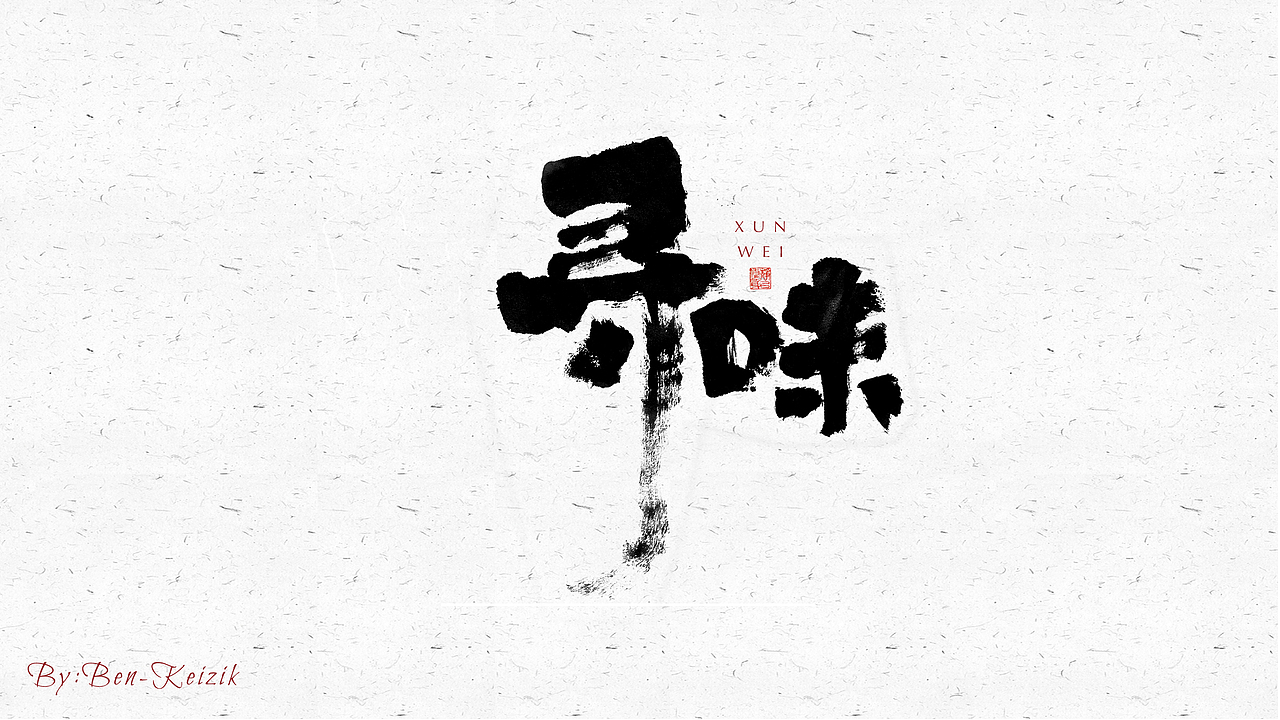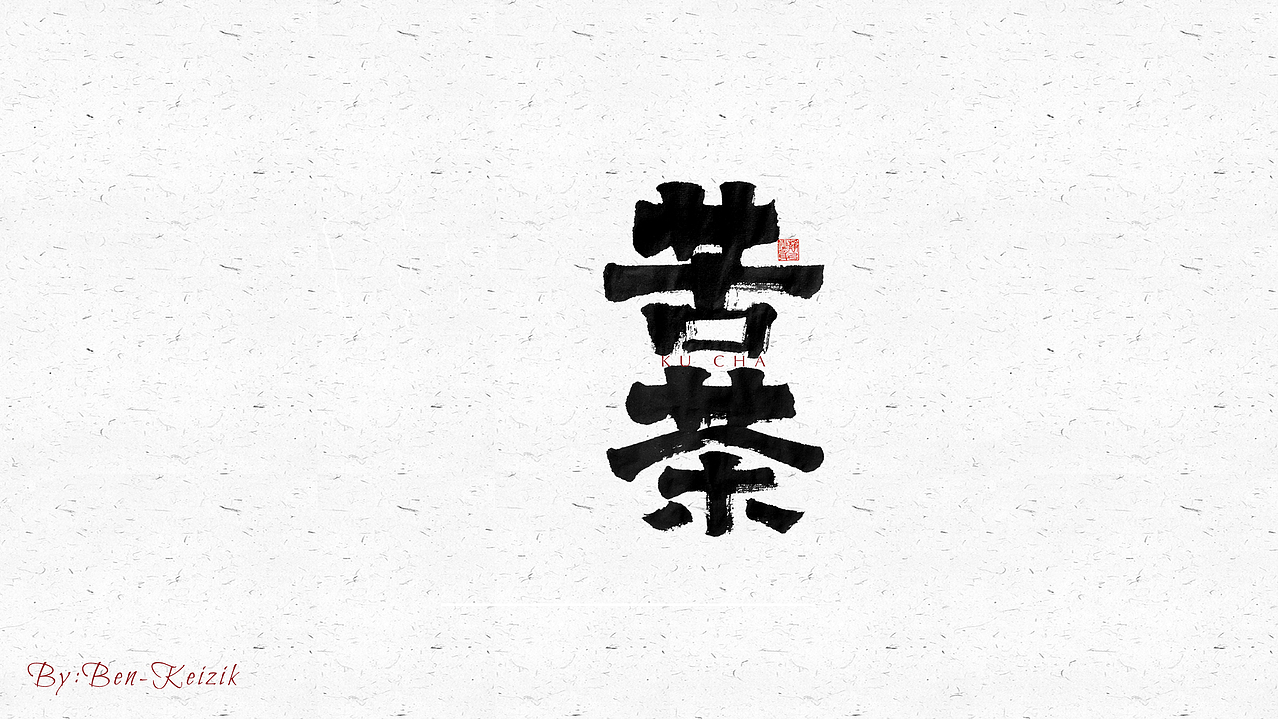
自言字语 —— 一组手写毛笔字(图ZMjUyNTg3OTk2) - 字体/字形 - 站酷设计师祺壹原创素材 - 站酷ZCOOL
自言字语 —— 一组手写毛笔字(图ZMjUyNTg4MDMy) - 字体/字形 - 站酷设计师祺壹原创素材 - 站酷ZCOOL
自言字语 —— 一组手写毛笔字(图ZMjUyNTg4MTIw) - 字体/字形 - 站酷设计师祺壹原创素材 - 站酷ZCOOL
自言字语 —— 一组手写毛笔字(图ZMjUyNTg4MDUy) - 字体/字形 - 站酷设计师祺壹原创素材 - 站酷ZCOOL
自言字语 —— 一组手写毛笔字(图ZMjUyNTg4MTMy) - 字体/字形 - 站酷设计师祺壹原创素材 - 站酷ZCOOL
自言字语 —— 一组手写毛笔字(图ZMjUyNTg4MTA4) - 字体/字形 - 站酷设计师祺壹原创素材 - 站酷ZCOOL
自言字语 —— 一组手写毛笔字(图ZMjUyNTg4MDQ0) - 字体/字形 - 站酷设计师祺壹原创素材 - 站酷ZCOOL
自言字语 —— 一组手写毛笔字(图ZMjUyNTg4MDA0) - 字体/字形 - 站酷设计师祺壹原创素材 - 站酷ZCOOL
自言字语 —— 一组手写毛笔字(图ZMjUyNTg4MTEy) - 字体/字形 - 站酷设计师祺壹原创素材 - 站酷ZCOOL
自言字语 —— 一组手写毛笔字(图ZMjUyNTg4MDI4) - 字体/字形 - 站酷设计师祺壹原创素材 - 站酷ZCOOL
自言字语 —— 一组手写毛笔字(图ZMjUyNTg3OTky) - 字体/字形 - 站酷设计师祺壹原创素材 - 站酷ZCOOL
自言字语 —— 一组手写毛笔字(图ZMjUyNTg4MDA4) - 字体/字形 - 站酷设计师祺壹原创素材 - 站酷ZCOOL
自言字语 —— 一组手写毛笔字(图ZMjUyNTg4MDM2) - 字体/字形 - 站酷设计师祺壹原创素材 - 站酷ZCOOL
自言字语 —— 一组手写毛笔字(图ZMjUyNTg4MDY4) - 字体/字形 - 站酷设计师祺壹原创素材 - 站酷ZCOOL
自言字语 —— 一组手写毛笔字(图ZMjUyNTg4MDg4) - 字体/字形 - 站酷设计师祺壹原创素材 - 站酷ZCOOL
自言字语 —— 一组手写毛笔字(图ZMjUyNTg4MTI4) - 字体/字形 - 站酷设计师祺壹原创素材 - 站酷ZCOOL
自言字语 —— 一组手写毛笔字(图ZMjUyNTg4MTAw) - 字体/字形 - 站酷设计师祺壹原创素材 - 站酷ZCOOL
自言字语 —— 一组手写毛笔字(图ZMjUyNTg4MDIw) - 字体/字形 - 站酷设计师祺壹原创素材 - 站酷ZCOOL
自言字语 —— 一组手写毛笔字(图ZMjUyNTg4MDE2) - 字体/字形 - 站酷设计师祺壹原创素材 - 站酷ZCOOL
自言字语 —— 一组手写毛笔字(图ZMjUyNTg4MDYw) - 字体/字形 - 站酷设计师祺壹原创素材 - 站酷ZCOOL
自言字语 —— 一组手写毛笔字(图ZMjUyNTg4MDg0) - 字体/字形 - 站酷设计师祺壹原创素材 - 站酷ZCOOL
自言字语 —— 一组手写毛笔字(图ZMjUyNTg4MDc2) - 字体/字形 - 站酷设计师祺壹原创素材 - 站酷ZCOOL
自言字语 —— 一组手写毛笔字(图ZMjUyNTg4MTE2) - 字体/字形 - 站酷设计师祺壹原创素材 - 站酷ZCOOL
自言字语 —— 一组手写毛笔字(图ZMjUyNTg4MTA0) - 字体/字形 - 站酷设计师祺壹原创素材 - 站酷ZCOOL
自言字语 —— 一组手写毛笔字(图ZMjUyNTg4MDky) - 字体/字形 - 站酷设计师祺壹原创素材 - 站酷ZCOOL
自言字语 —— 一组手写毛笔字(图ZMjUyNTg4MDU2) - 字体/字形 - 站酷设计师祺壹原创素材 - 站酷ZCOOL